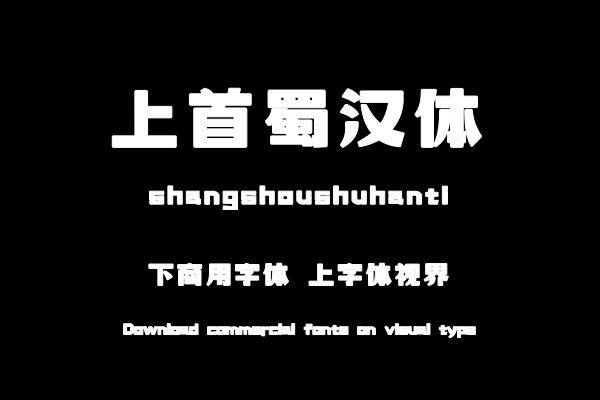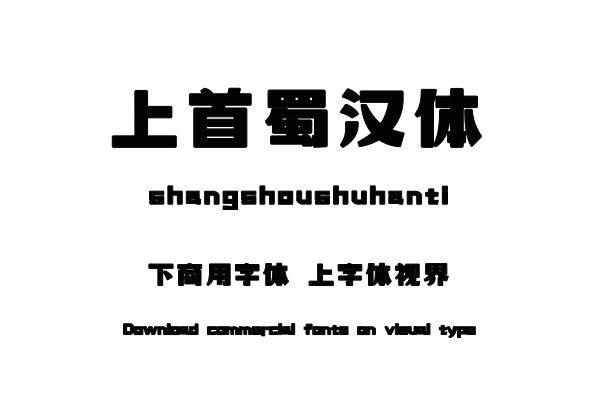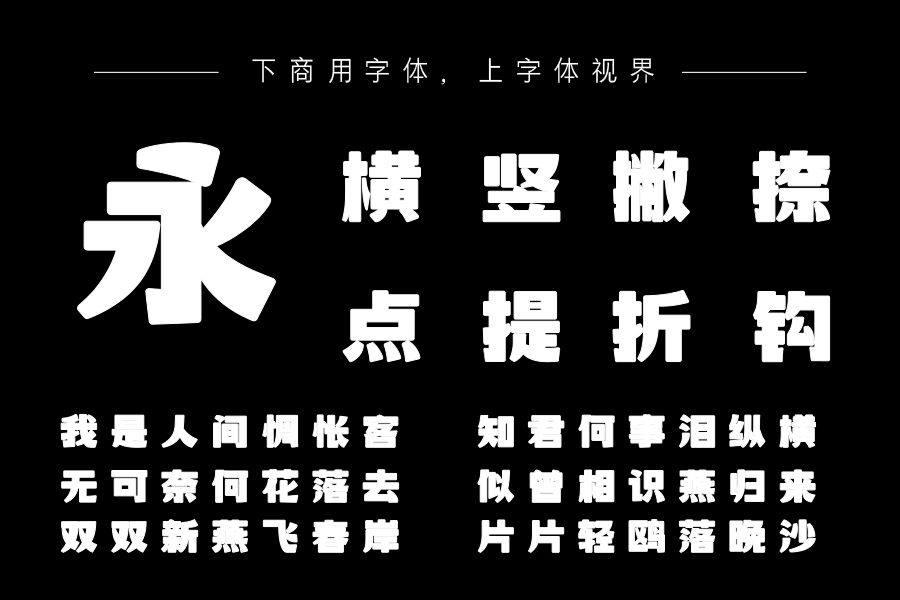
上首蜀汉体,简体中文约6763字,此套字整体更倾向于黑体的形式,笔画采用了独特的构思,每个笔画的顶点恰当的进行了平滑处理,使得整个字更加圆滑;稳重。斜线用了弯曲......购买须知:“下载服务费”与“字体VIP”所获得字体 仅用于个人非商用, 商用请联系付费授权。本字体为电脑用字,手机没有root权限不支持直接手机换字(手机如何root,请自行百度搜索教程)。购买前请先 了解清楚后再付款 ,字体为虚拟产品无法回收 一旦购买不支持退款。